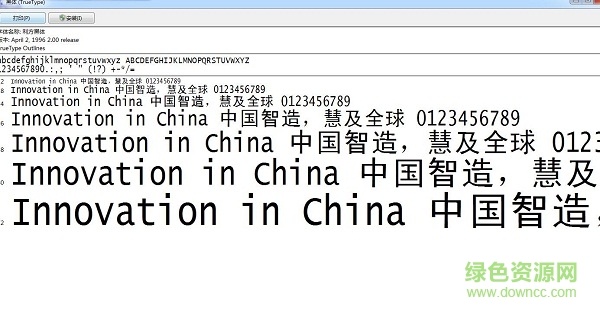
rs_hei 字體又叫利方黑體字體,這是一款非常樸素的實用性字體,干凈簡潔粗細相等,綠色資源網(wǎng)匯聚了大量的廣告字體、海報字體、書法字體、商業(yè)字體等一系列好看的字體,歡迎下載!
漢字的黑體是在現(xiàn)代印刷術(shù)傳入東方后依據(jù)西文無襯線體中的黑體所創(chuàng)造的。由于漢字筆劃多,小字的黑體清晰度較差,所以一開始主要用于文章標題,但隨著制字技術(shù)的精進,已有許多適用于內(nèi)文的黑體字型。